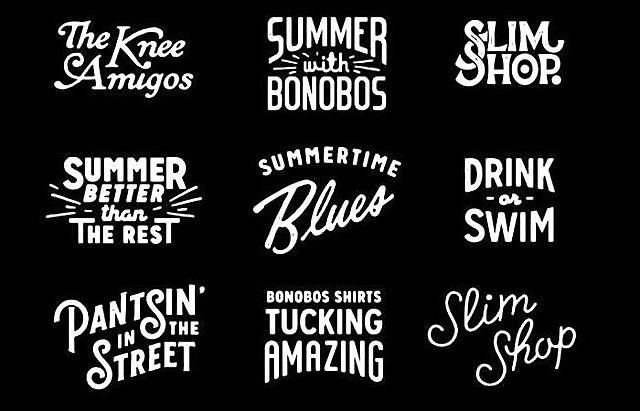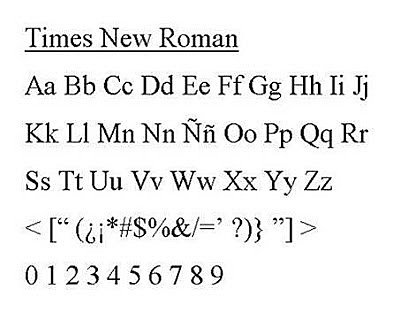
Va desde los 3000 A.C. en donde el sistema pictográfico trataba de imitar formas naturales, dibujadas para representar por ejemplo acciones de la vida cotidiana, luego estos pictogramas haciéndose cada vez más abstractos y adaptándose a las herramientas y soportes de la época, empiezan a transformarse en letras. Era muy distinto tallar en piedra, con una herramienta estilo cincel, a escribir sobre un papiro, con un soporte mas suave y con una tinta liquida.
Luego los romanos inventaron las letras con serif, quizás por la herramienta (el cincel) que utilizaban para tallar las letras en los monumentos hechos en piedra, mármol, etc. o probablemente por razones estéticas.
Luego, en el 200 A.C. aparecen las letras capitales, por ejemplo los textos griegos no utilizaban espacios entre letras, así todos los textos estaban escritos en "mayúsculas" y aun no existían las letras minúsculas.
Es un año importante para la evolución de la tipografía gracias a la invención de la imprenta, creada por Johannes Gutenberg, el apostó por crear un sistema de reproducción de libros a corto tiempo, y hacer todos los ejemplares exactamente iguales. Adaptó la xilografía (técnica para reproducir impresos con una matriz de madera), el sistema de una la prensa de vino, y la creación de tipos en metal. La primera producción sería imprimir varios ejemplares de la Biblia.
Una de las tipografías más extendidas e influyentes de la historia y también una de las mejores romanas jamás creadas fue la diseñada por Claude Garamond en el siglo XVI en Francia. Fue votada como la tipografía del milenio en una encuesta celebrada entre profesionales. Existe un perfecto equilibrio entre elegancia y sentido practico.
Nicholas Kis Teólogo, E Amsterdan aparte de diseñar y grabar tipos realizo la Biblia Húngara (1686) , y el nuevo testamento 1887). Fue un diseñador de tipos, grabador de punzones, impresor y editor pero sobre todo fue un visionario cultural que persiguió la belleza a través de tipos y con la impresión de libros.
Caslon se refiere a una extensa familia de tipos de letra que se originan en los tipos dibujados y fundidos por el tipógrafo inglés William Caslon. La primera tipografía Caslon fue diseñada en 1725 por el inglés William Caslon. Sus influencias fueron los diseñadores holandeses Christoffel van Dijcksy Dirck Voskens. Se trata de una tipografía cálida y muy confortable para el ojo lo que la hace altamente legible.
Tipografía clave dentro del estilo moderno aparecido a finales del siglo XVIII culminación de 300 años de evolución de la tipografía romana.Giambattista Bodoni fue denominado Rey de los Impresores gracias a la exquisita calidad de sus impresos. Su aparición desplazó a las tipografías antiguas y transicionales gracias al contraste existente entre las líneas finas y gruesas, sus remates delgados y rectos y su apariencia clara y racional.
Esculpe letras en piedra y también en madera para los títulos de las portadas de los libros, Eric Gill comienza a diseñar tipos para imprenta solamente después de una gran labor de persuasión ejercida sobre él por Stanley Morison, ya que como él decía la tipografía no era su campo de actuación y no tenía ninguna experiencia sobre el tema. Algunos tipos son
• Gill Sans series 231 (1928)
• Perpetua (1929)
• Solus (1929)
• Golden Cockerel Roman (1930)
• Hague & Gill Joanna (1930)
• Bunyan (1934) -
Morris Fuller Benton es probablemente uno de los tipógrafos más importantes en la historia de la tipografía, siendo el creador de diversas tipografías que hoy día se utilizan. Algunas de ellas son:
• Century Expanded (1900)
• Linotex (1901)
• Century Oldstyle (1908-1909)
• Hobo (1910)
• Parisian (1928)
• Novel Gothic (1928)
• Chic (1928)
• Modernique (1928)
• Broadway (1928)
• Tower (1934)
• Phenix (1935) -
Es una tipografía sans serif diseñada por Paul Renner en 1927. Futura es uno de los tipos de letra más conocidos y utilizados de las tipografías modernas. Es considerada una de las aplicaciones de la Nueva Tipografía. Fue muy usada a mediados del siglo XX y continúa siendo muy popular en la actualidad
En 1931, después de que Stanley Morison escribiera un artículo criticando al periódico The Times por estar mal impreso y tipográficamente anticuado, fue contratado para diseñar una nueva tipografía para este periódico. El nuevo diseño fue supervisado por Stanley Morison y dibujado por Víctor Lardent, un artista del departamento de publicidad de The Times. Como base para su diseño utilizó la tipografía Plantin pero con muchas modificaciones para conseguir más legibilidad y economía de espacio.
Luego en el siglo XX, llega la era digital, las computadoras y el internet, el uso de nuevos dispositivos que a grandes pasos han ido evolucionando, creando nuevas maneras de lectura, es por eso que la tipografía empieza a adquirir nuevas características especiales para estas plataformas, por ejemplo la creación de tipografías seguras, que son especiales para todos estos medios y soportes, es como una especie de consenso mundial, que hace que la lectura sea segura para todos los lectores.